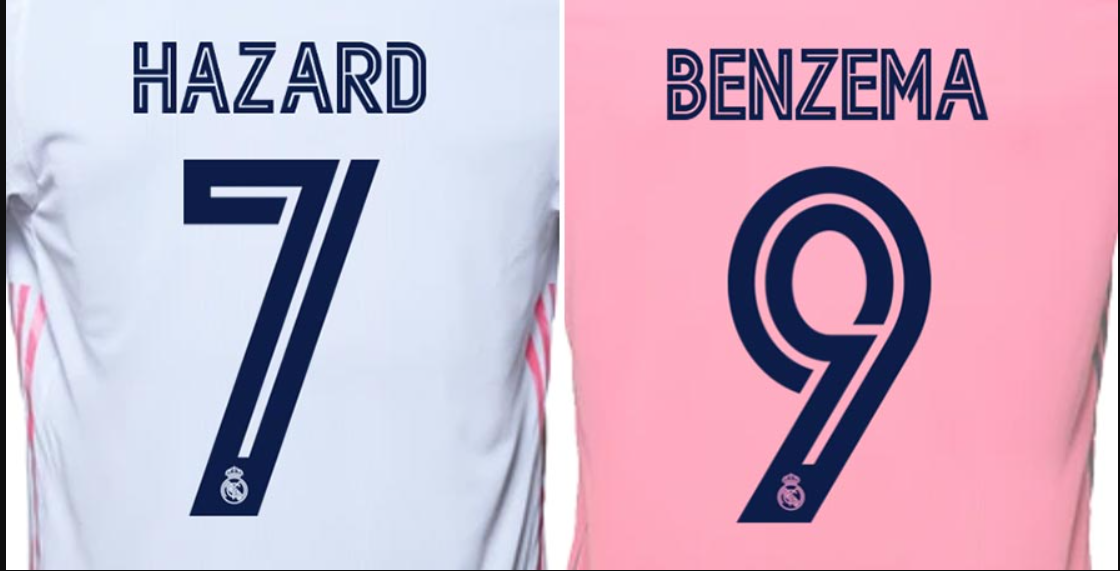
Reviva uma das temporadas marcantes dos Merengues com a tipografia correta. A temporada 2020/2021 trouxe uniformes que equilibraram a sobriedade clássica do Real Madrid com toques modernos de design, assinados pela parceira de longa data, a Adidas.
Este post traz o arquivo da fonte utilizada pelo clube nas competições europeias (como a UEFA Champions League) e na Copa do Rei. Diferente da fonte padronizada da La Liga, esta versão carrega a identidade visual exclusiva criada pela marca alemã para o clube, perfeita para quem busca autenticidade máxima na personalização.
Estilo Visual e Aplicação
A tipografia do Real Madrid para a temporada 20/21 se destaca pelo seu peso e presença. É uma fonte Sans Serif (sem serifa) robusta, com traços grossos e geométricos que garantem excelente legibilidade à distância.
Um detalhe interessante deste design da Adidas é a inspiração na arquitetura moderna e na cultura urbana de Madri, fugindo do estilo “pincelado” de temporadas anteriores. Nas costas da camisa branca tradicional ou do uniforme rosa (Away), essa fonte transmite força e estabilidade, características sempre associadas ao maior campeão da Europa.
Dica de Ouro: Esta fonte é ideal para reproduzir as camisas de ídolos daquela temporada, como Benzema, Sergio Ramos e Vinícius Jr.